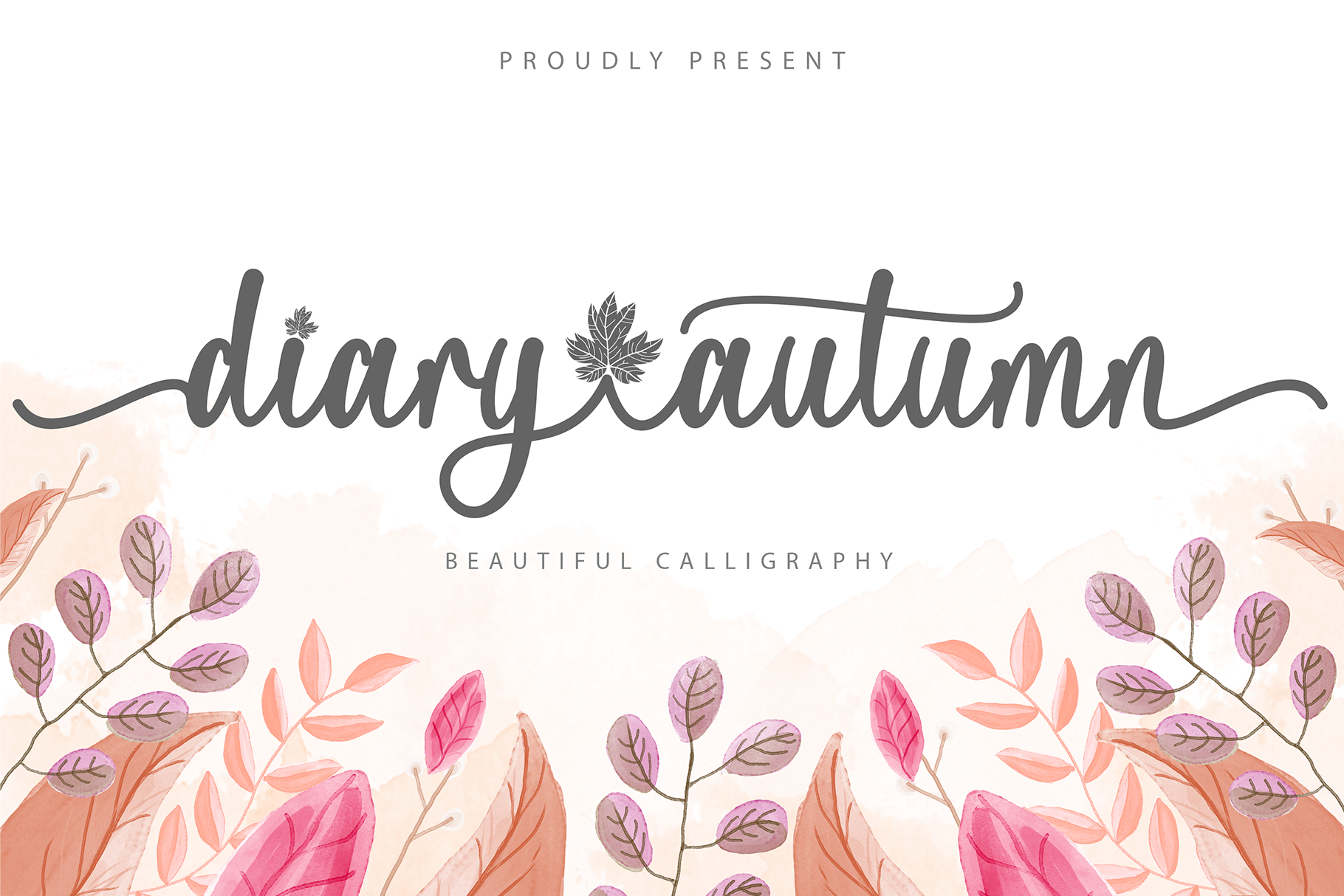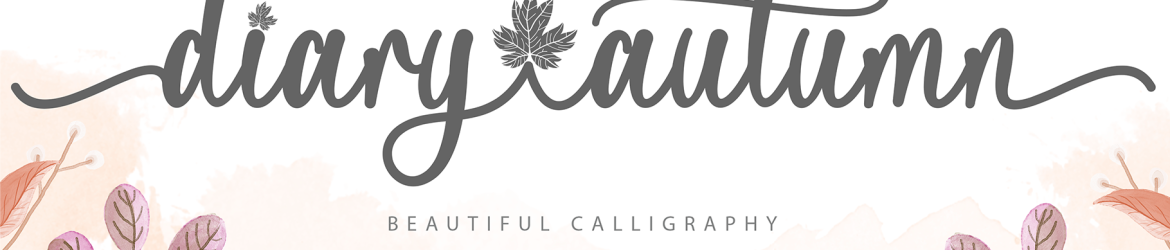
Diary Autumn é uma elegante caligrafia à mão delicada que traz ao seu design escrita de forma única e equilibrada. Perfeito para quem busca expressar sentimentos ou detalhes com sutileza, este script se destaca como um trabalho de arte em si. O fato de ser PUA (Propriedade Universal Associada) significando que você pode ter acesso a todos os caracteres e variações com facilidade. Seja para usar em anotações pessoais ou artigos de literatura, esta fonte se torna uma ferramenta valiosa no seu arsenal gráfico. Yoga Letter criou algo singular aqui, um toque autêntico na escrita que vai além das letras simples e transformá-las em elementos únicos. Não deixe de experimentar Diary Autumn para adicionar um toque único a suas criações.